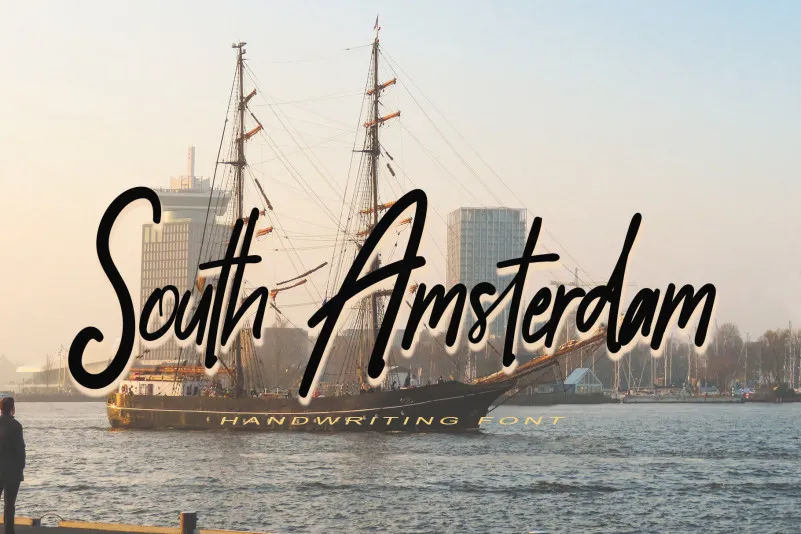
Esta é uma linda fonte escrita à mão. Ela possui um charme autêntico que fará você cair de amores por ela e a colocará ao seu lado para criar cartões de aniversário adoráveis, arte de cartão de visita encantadora, postagens em redes sociais chamativas e convites de casamento lindos. A fonte “South Amsterdam” foi criada pelo designer KateEngciu e se encaixa perfeitamente na categoria de fontes escrita à mão. Seja você um designer ou amante da arte, essa fonte vai transformar seus projetos digitais em algo verdadeiramente especial, encantador e único. Seja para criar cartões de aniversário personalizados para familiares especiais ou convites de casamento exclusivos que irão fazer as pessoas rirem ao lerem; seja para criar postagens de redes sociais sobre seu trabalho, seu hobby ou sua vida pessoal; seja para adicionar um toque especial à arte do cartão de visita. A fonte “South Amsterdam” é perfeita para qualquer projeto que você possa imaginar.